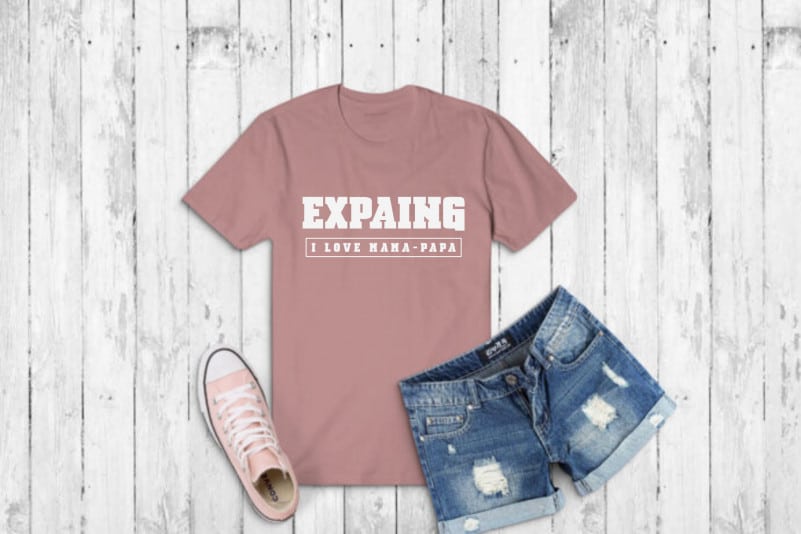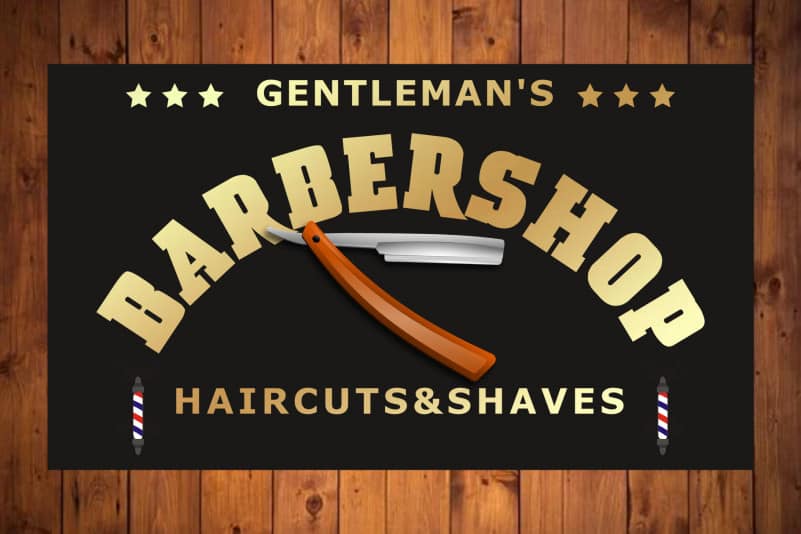
Expaing Slab Serif Font
Expaing Slab Serif Font adalah font tebal, namun canggih yang menampilkan karakter tebal dan panjang yang akan terlihat sangat mahir saat digunakan dalam logo, branding, majalah mode, desain pernikahan, posting media sosial, iklan, kemasan produk, desain produk, label, fotografi, desain kemasan, dan banyak lagi. Font tampilan yang dirancang dengan ahli ini benar-benar harus dimiliki. Ini berisi huruf besar, huruf kecil, angka, tanda baca, simbol, dan dukungan multibahasa.